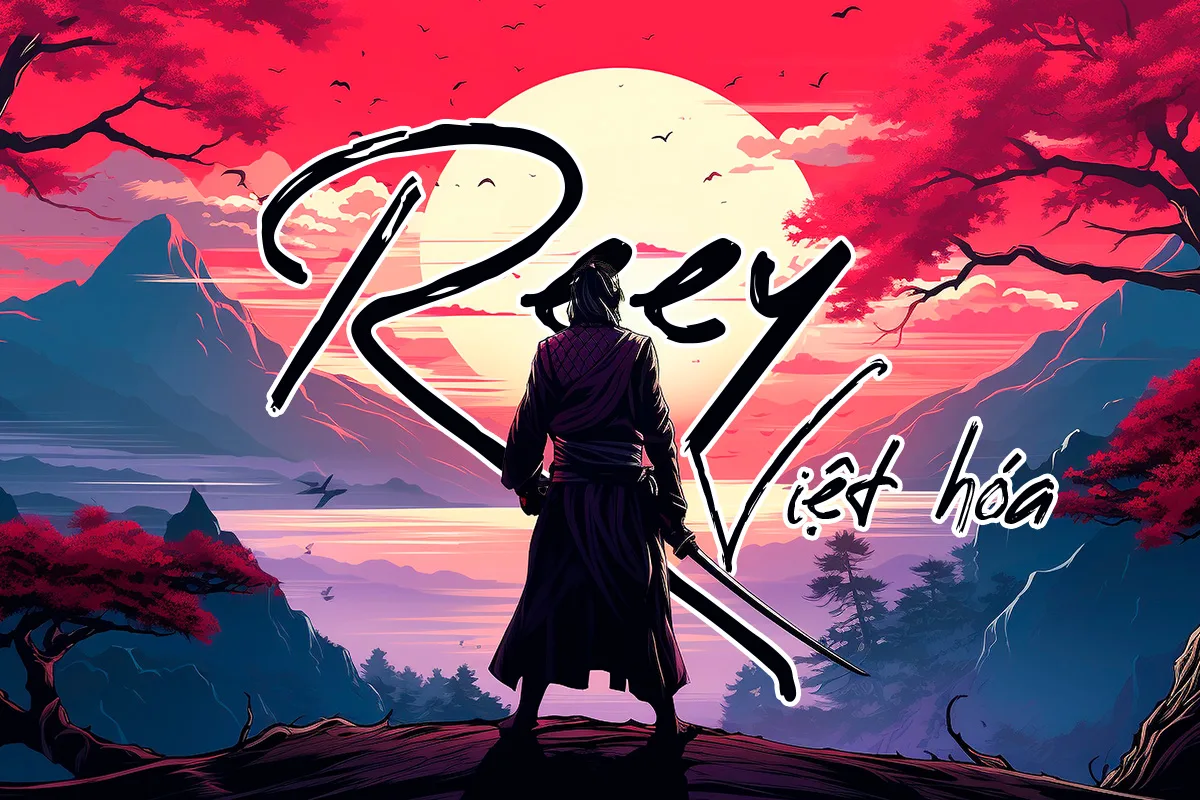
Reey Việt Hóa là một font chữ ký (signature font) phong cách brush script mang đậm tinh thần tự do, mạnh mẽ và nghệ thuật. Với những nét cọ bay bổng, thanh thoát nhưng vẫn giữ độ chắc khỏe, Reey tạo nên cảm giác như được viết bằng tay trên nền giấy bằng cọ thật — vừa phóng khoáng, vừa có điểm nhấn riêng biệt.
Font đặc biệt phù hợp cho các dự án cá nhân, thiết kế logo, chữ ký, bao bì sản phẩm, poster nghệ thuật, hoặc typography trong ảnh quảng cáo. Khi được Việt hóa, Reey vẫn giữ trọn vẹn sự tự nhiên của bản gốc, đồng thời hỗ trợ đầy đủ dấu tiếng Việt, giúp người dùng dễ dàng ứng dụng trong các thiết kế mang bản sắc Việt.